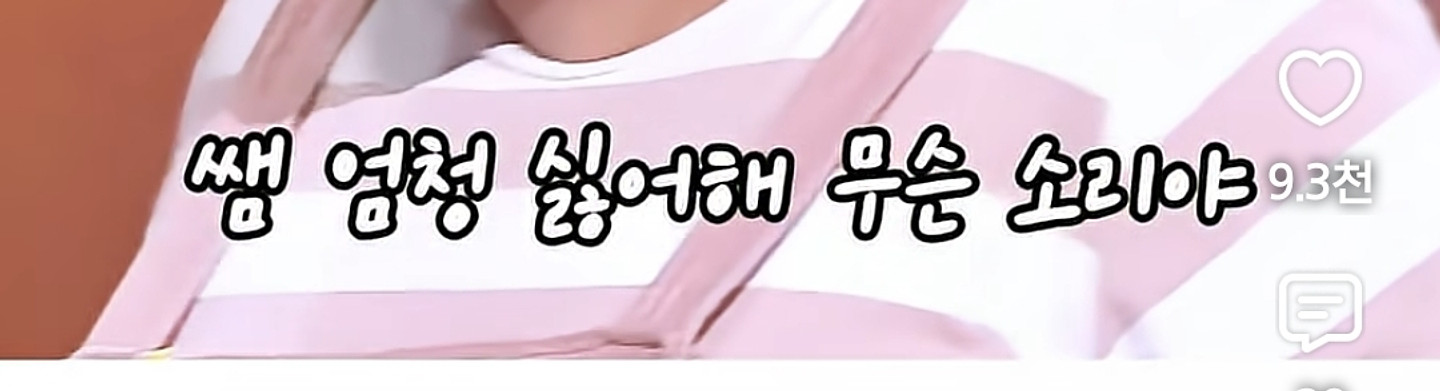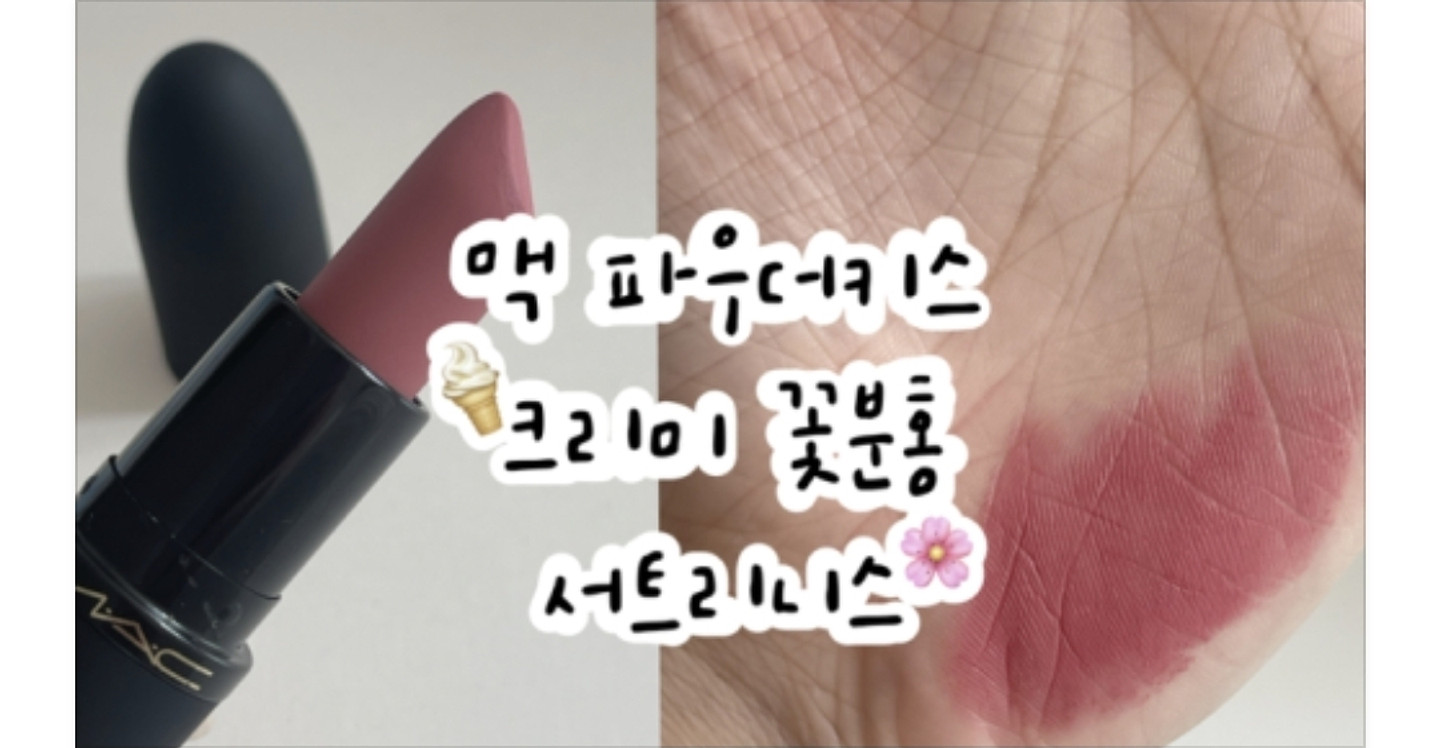
아시는분 계실까요
아이폰 카카오톡에 쓰던 폰트인데 찾아주세요 ㅠ 오른쪽은 카톡 제목이라 좀 굵게 보이고, 원래는 왼쪽처럼 보입니다! 하트가 저런 게 특징인데 비슷한 것들만 보이고 못 찾겠어요 ㅠㅠ 몇 년 전에 해두었다가 얼ㅁ ㅏ전 아이폰 ios 업뎃했더니 갑자기 초기화가 돼버렸어요